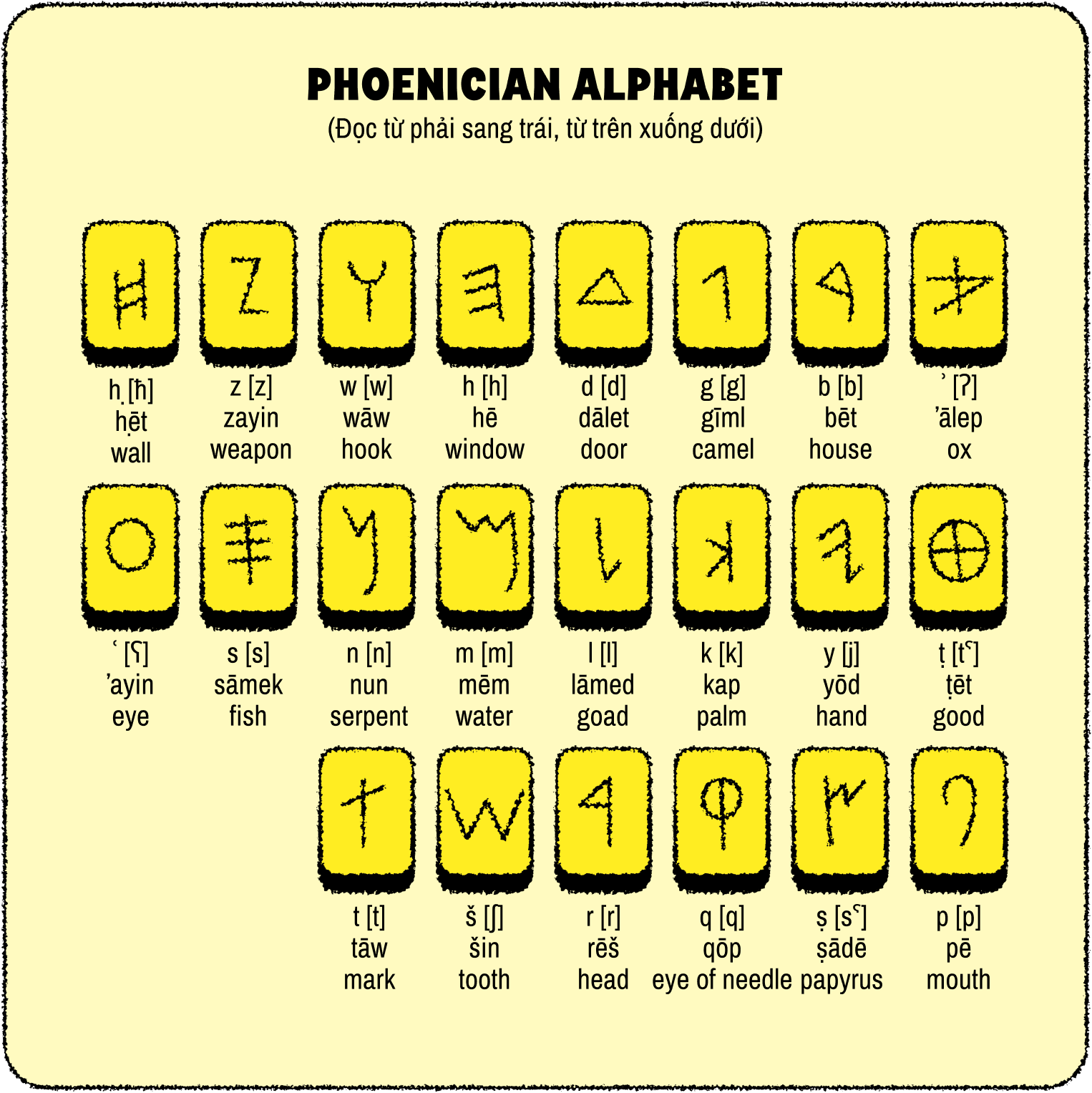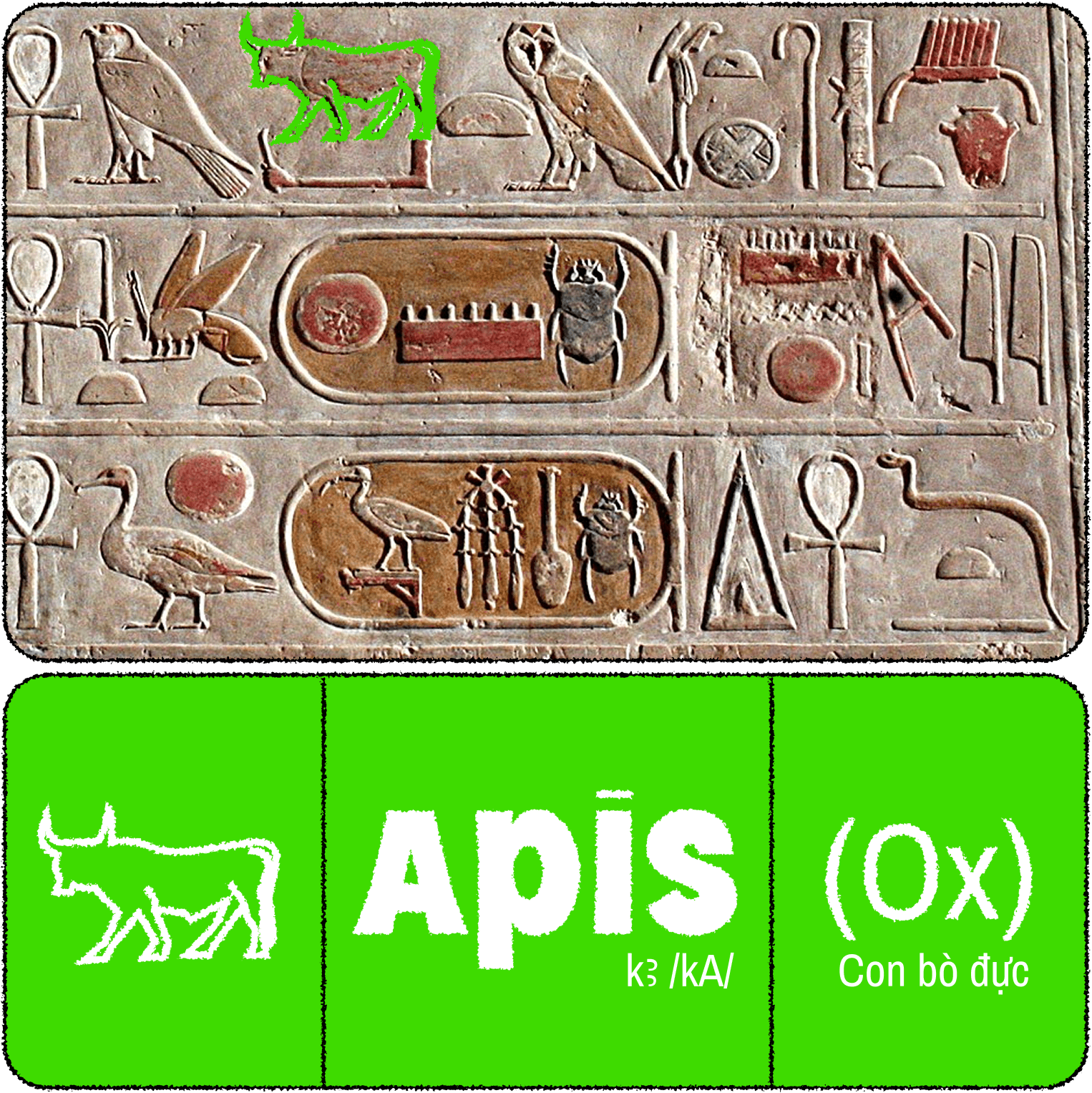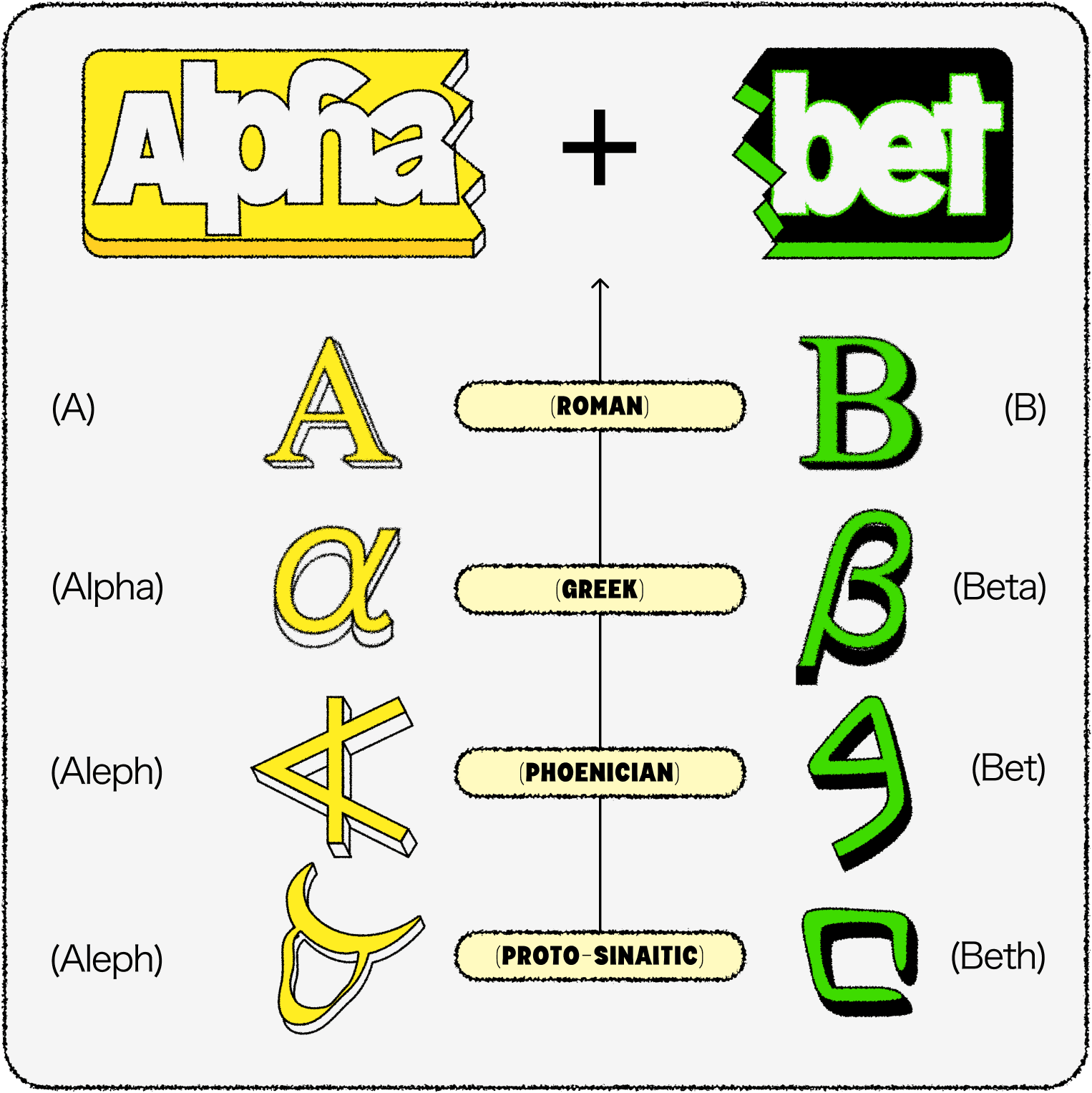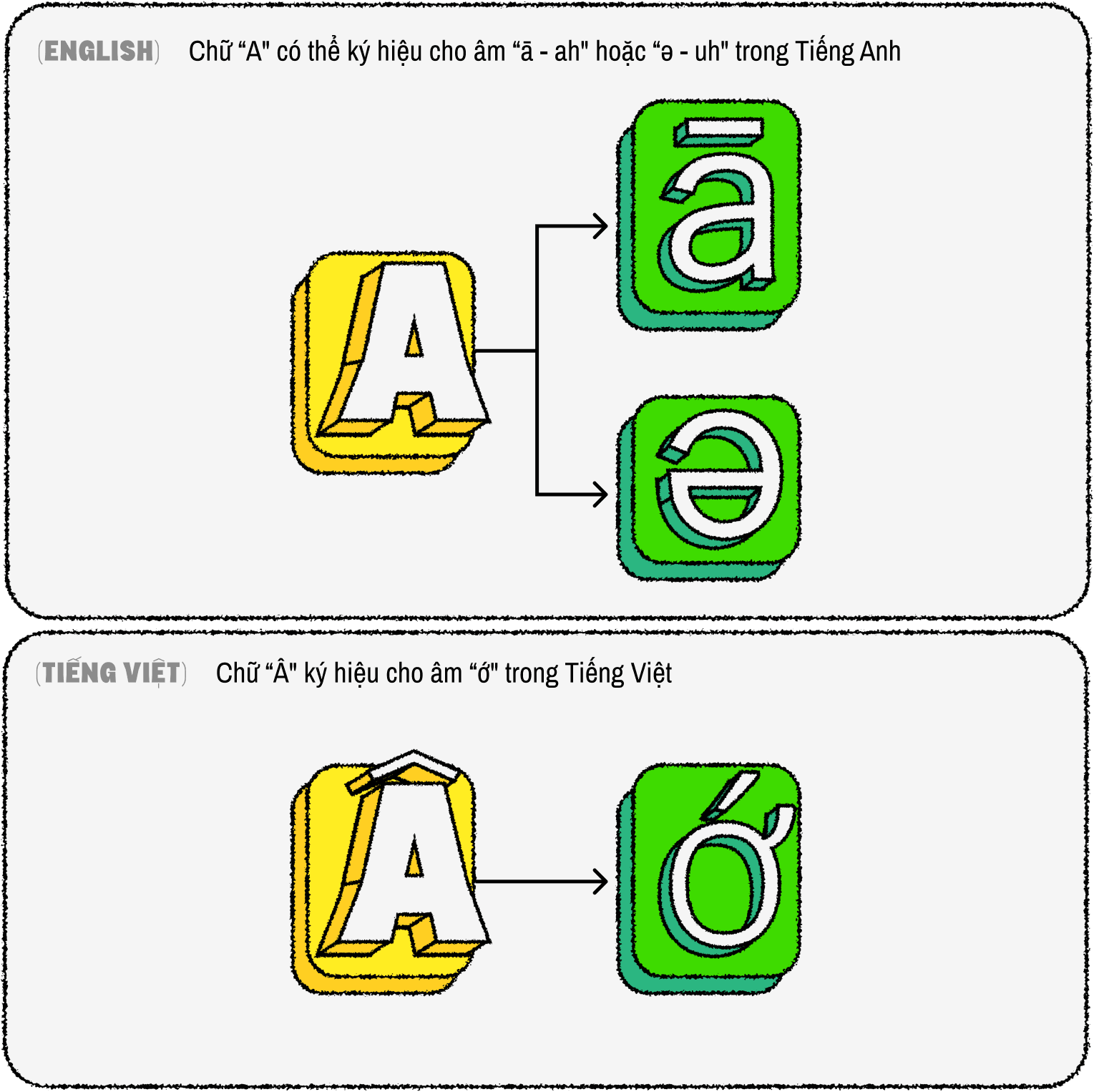
ALPHABET (Bảng chữ cái) là một chuỗi hệ thống các ký hiệu, ký tự được thống nhất về mặt văn hoá nhằm đại diện cho những thanh âm cụ thể.
Trước khi được phát triển bởi người Phoenicia (một nhóm thương nhân đi biển sống ở Lebanon ngày nay) vào khoảng năm 1500 TCN, một ký hiệu được sử dụng trong ngôn ngữ viết thường diễn tả một ý nghĩa trọn vẹn mà không dựa trên cách phát âm của chúng, hay còn được biết tới là dạng chữ tượng hình.
Điều đó có nghĩa, để có thể viết hay lưu lại ngôn ngữ nói, chúng ta cần ghi nhớ hàng ngàn ký hiệu đại diện cho từng hình ảnh khác nhau. Việc phát triển ra một hệ thống ký hiệu tượng âm thay vì tượng hình hay tượng ý giúp người Phoenicia ghi lại toàn bộ ngôn ngữ của họ chỉ trong 22 ký tự.
Thuật ngữ ALPHABET được tạo thành từ tên của 2 chữ cái đầu tiên trong bảng chữ cái Hy Lạp là alpha (α) và beta (β). Tên của hai chữ cái alpha (α) and beta (β) lại có nguồn gốc từ tên của hai chữ cái đầu tiên trong bảng chữ cái Phoenician là aleph (có nghĩa là con bò đực), và bet (có nghĩa là ngôi nhà).
Điều này cho thấy chỉ xét riêng cụm chữ “ALPHABET" cũng đã khái quát được phần nào quá trình hình thành và phát triển của ngôn ngữ, một quá trình luôn có sự giao thoa và kế thừa từ nhiều nền văn minh khác nhau, qua thời gian, chúng trở thành một hệ thống được thống nhất về mặt văn hoá, và chúng ta chia sẻ chúng cùng nhau.